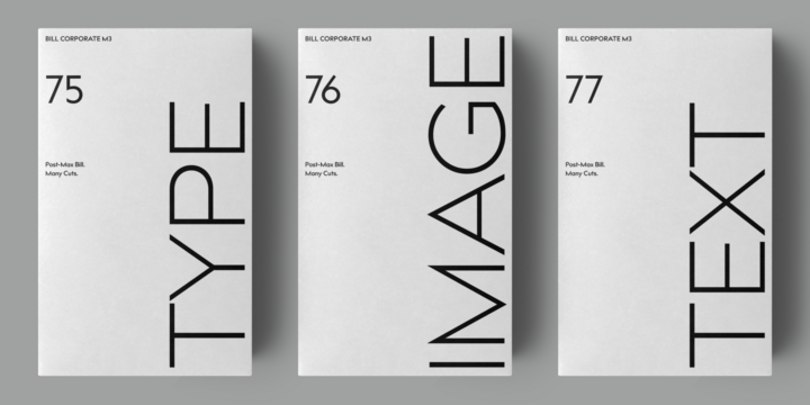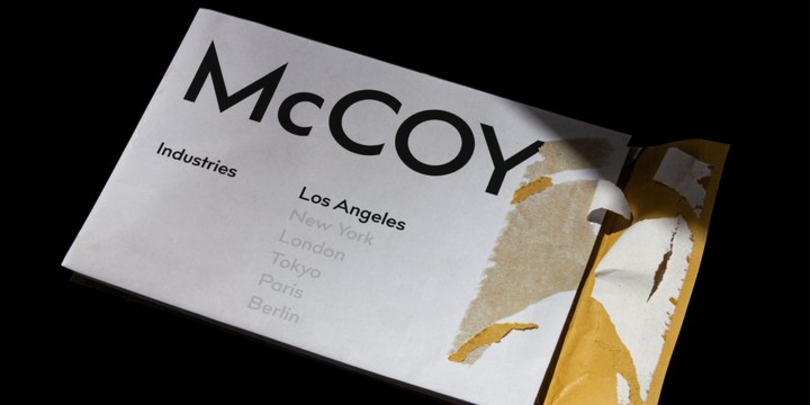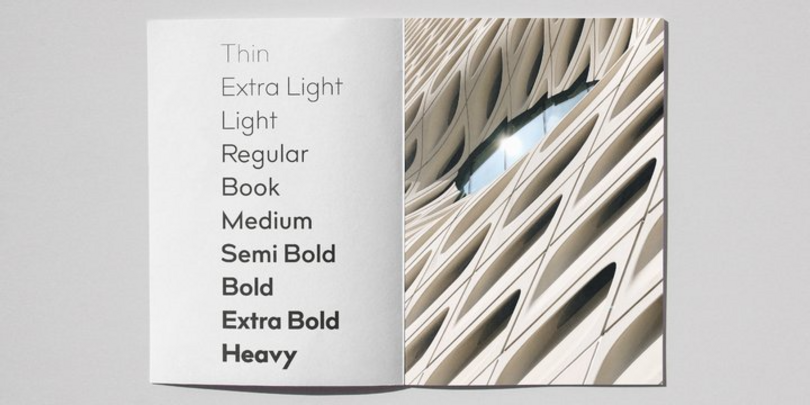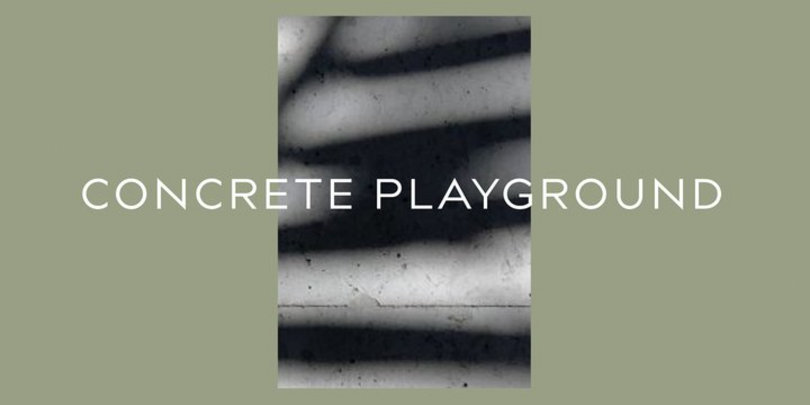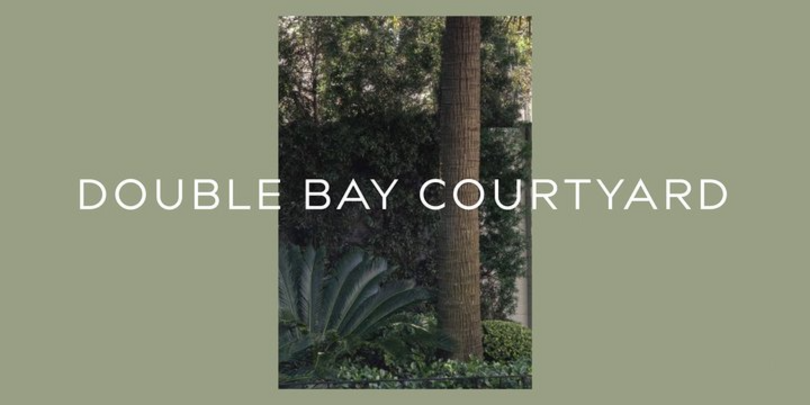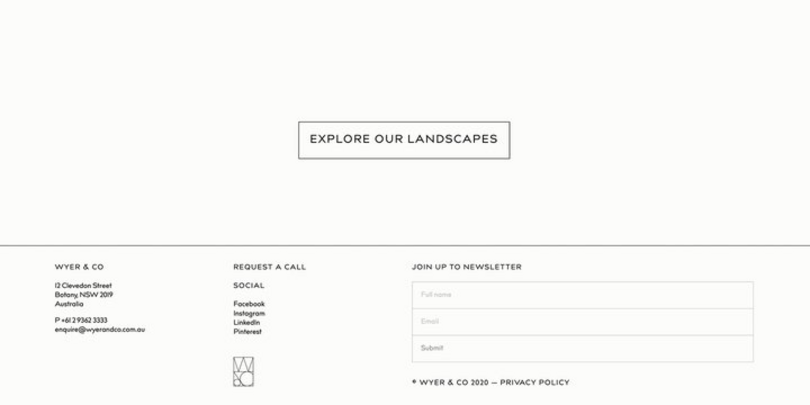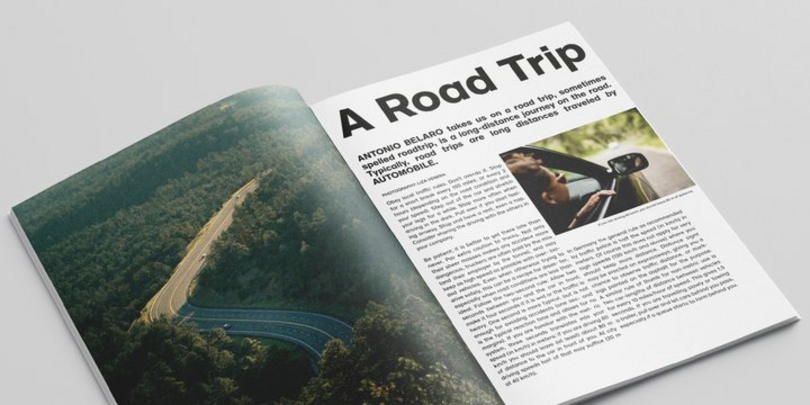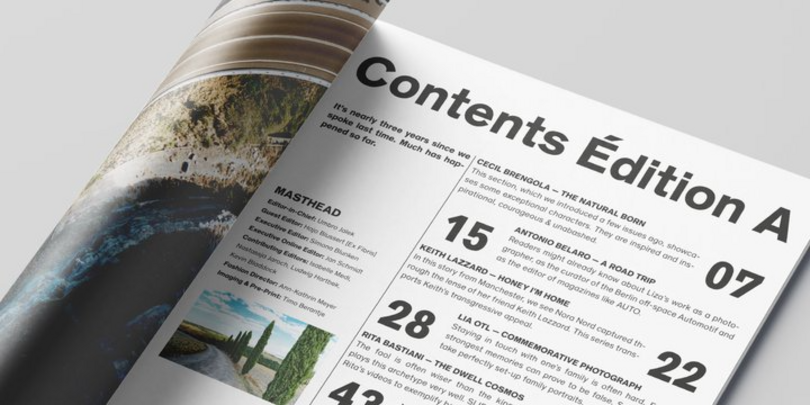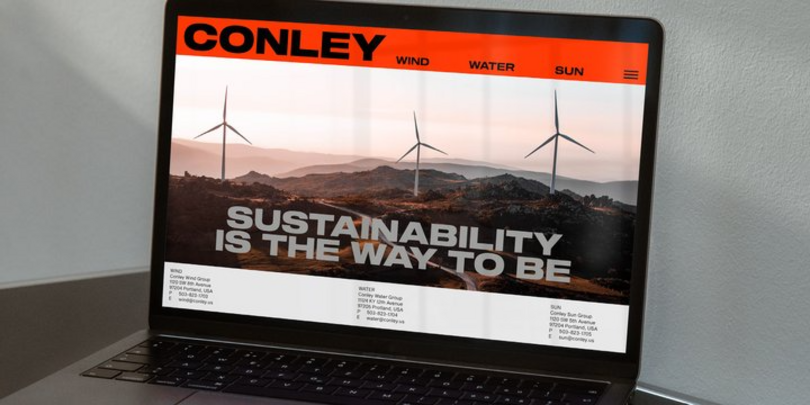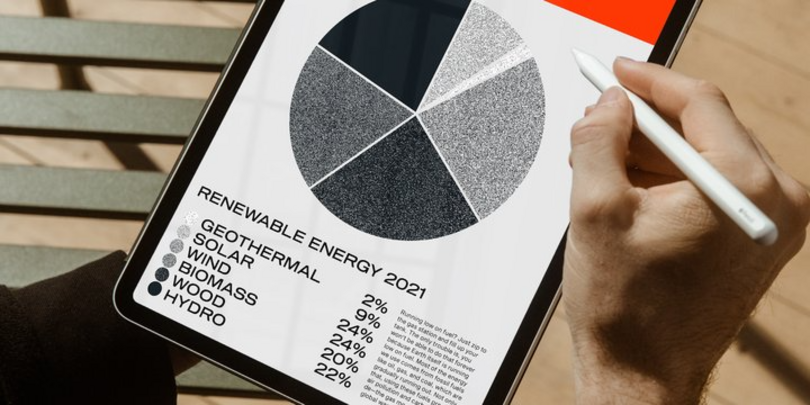
Points forts de la fonderie OGJ Type.
OGJ Type.
OGJ Type Design est une fonderie typographique basée à Berlin, en Allemagne. Elle se spécialise dans la conception de polices système et de polices personnalisées pour un large éventail de clients : des designers indépendants aux grandes marques de consommation à travers l'Europe et l'Amérique. OGJ est fière d'être la seule distributrice officielle de la bibliothèque de polices Max Bill et de collaborer avec la fondation Max Bill Georges Vantongerloo afin de développer de nouveaux designs « post-Max Bill » à la hauteur des idées originales de Bill. Depuis 2015, la fonderie a créé des polices de caractères intemporelles, toutes conçues en gardant les utilisateurs à l'esprit. La qualité du travail est à l'honneur, tandis que l’œil expert d'Oliver Jeschke permet d'assurer une valeur élevée et constante du produit, conformément à l'adage « la qualité avant la quantité ».
Sequel Sans
Sequel Sans est une nouvelle venue au sein de la famille des polices de caractères néo-linéales. Créée en collaboration avec la fondation Max Bill Georges Vantongerloo, elle s’inspire des polices de caractères sans serif utilisées par Max Bill, l’architecte, artiste et designer suisse hors du commun. Gardant cette trame, Sequel Sans se veut une famille de polices propre et adaptable qui repose sur un système complet de styles. À l’image des grandes polices néo-linéales que l’on peut retrouver dans les designs de style suisse du milieu du siècle dernier, Sequel Sans est prête à l’emploi pour n’importe quel type de contenu. Elle amplifiera votre message tout en conservant son propre caractère moderniste.
Sequel 100 Black
Sequel 100 Black est une police de caractères néo-linéale destinée aux gros titres percutants, aux titres résolus et aux affiches remarquables. Dérivée de Sequel Sans et conçue avant tout pour le titrage, elle présente des proportions plus larges que sa police d’origine. Elle dispose également d’une hauteur d’x plus élevée pour offrir un maximum d’impact sur la page. Et cette police de caractères n’est pas un poids plume : il s’agit de la plus épaisse au sein de la superfamille Sequel, avec des graisses qui commencent à 45 (un style moyen robuste) jusqu’à un 115 ultra-noir. Utilisez Sequel 100 Black dès que vous souhaitez associer une touche de modernisme tendance du milieu du siècle à la tension scintillante produite par une utilisation maximale de l’encre et un espace blanc minimal.
Sequel 100 Wide
Sequel 100 Wide est une police statique sans serif ou néo-linéale présentant des proportions horizontales généreuses. Cette variante de la police originale Sequel Sans étend considérablement la portée stylistique de la superfamille Sequel. Outre ses formes de lettres plus larges, elle dispose d’une hauteur d’x plus élevée ancrant la police dans un style historique rappelant davantage les années 1960 que 1950. Pourtant, elle est véritablement aussi nette et fonctionnelle que la famille de polices principale, avec des terminaisons de fûts parfaitement horizontales et verticales. Elle dispose par ailleurs de six graisses allant de 45 (Regular) à 95 (Black), d’italiques assortis et d’un nombre illimité d’interpolations possibles grâce à deux polices variables offrant une riche palette typographique pour toutes les situations.
Temper Wide
Temper Wide est une police slab néo-linéale étendue présentant un serif sans congés et des points carrés. Cette police de caractères transpose au XXIe siècle les styles des années 1960, comme le lettrage chromé des voitures classiques. Ses formes de lettres robustes et son héritage industriel lui confèrent un look sans fioritures, parfaitement adapté au design éditorial et à la publicité. Police de caractères neutre et sans fioritures, Temper Wide constitue une toile de fond énergique pour la mode et les accessoires, que ce soit en matière de produits, de campagnes ou d’identité de marque.
Bill Corporate Medium
Bill Corporate, classique moderne basé sur le travail de lettrage de Max Bill, est une police de caractères géométrique dotée d’une construction simple et inflexible à la fois audacieuse et grandiose. Avec ses formes de lettres minimalistes, ses pointes effilées et ses proportions archétypales, cette famille de polices ne suit aucune tendance. Elle cherche plutôt à atteindre un look intemporel et élégant. La silhouette de ses lettres s’inspire fortement des célèbres formes primaires du Bauhaus : le carré, le cercle et le triangle, ce qui donne des majuscules larges et des minuscules beaucoup plus étroites. Les majuscules, avec leurs largeurs variées et leurs dimensions généreuses, conviennent aux logotypes et aux mots-symboles raffinés.
JT Collect
JT Collect est une police de caractères sans serif hybride qui adopte une approche ludique du patrimoine typographique de l’Allemagne et de la Suisse. Créée avec assurance à partir d’une structure géométrique et imprégnée d’éléments issus de polices de caractères linéales traditionnelles, elle se trouve à mi-chemin entre géométrie et grotesque. Ses six graisses et trois tailles optiques offrent de nombreuses possibilités. Bien qu’elles soient simples et élégantes dans la version Light weight, les polices deviennent plus présentes sur la page à mesure que leur trait s’épaissit. La graisse Book se prête idéalement aux textes courts et de longueur moyenne, tandis que la puissante Bold rend les mots-symboles plus nets et permet aux titres d’afficher une assurance cosmopolite.
Bill Corp M3
Bill Corporate M3, une police de caractères géométrique sans serif, est une variante de la police Bill Corporate Medium de Max Bill. La famille se décline en 23 styles, tandis que la police de caractères est compatible avec les langues d’Europe centrale, orientale et occidentale.
Shapiro
Police néo-linéale évoquant distinctement le style du milieu du siècle, Shapiro est parfaite pour tout écrit nécessitant une expression contenue, mais confiante. Cette police de caractères linéale présente des fûts horizontaux et verticaux qui possèdent presque la même largeur. La police variable multi-axes de Shapiro comprend 8 graisses de texte, du clair au noir, ainsi que trois tailles supplémentaires (« Headline », « Display » et « Max »), espacées pour les applications plus importantes. Shapiro Pro compte parmi les autres ajouts à la famille. Il s’agit d’une police linéale intéressante proposée en 16 styles allant du léger au gras. On peut également citer Shapiro Base, une police de caractères à la coupe plus marquée qui constitue un bon point de départ pour tout projet portant sur l’identité de marque.